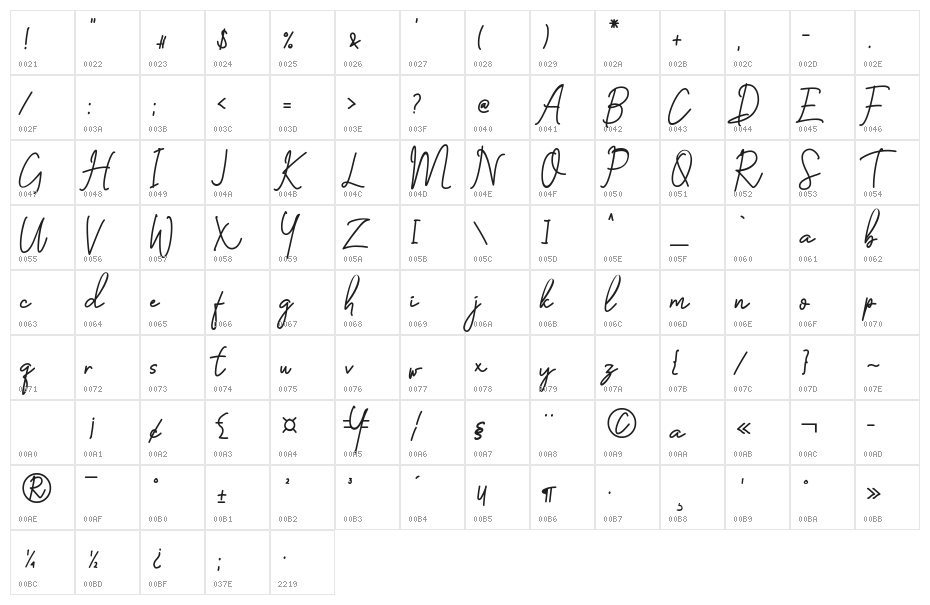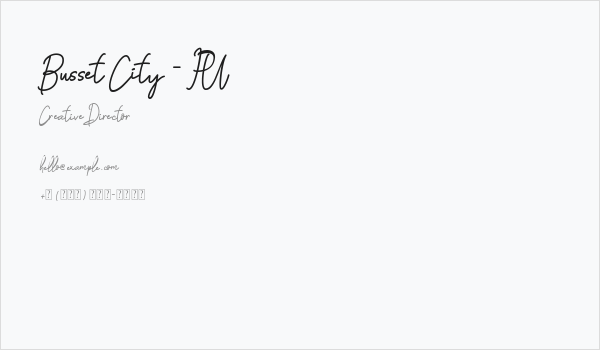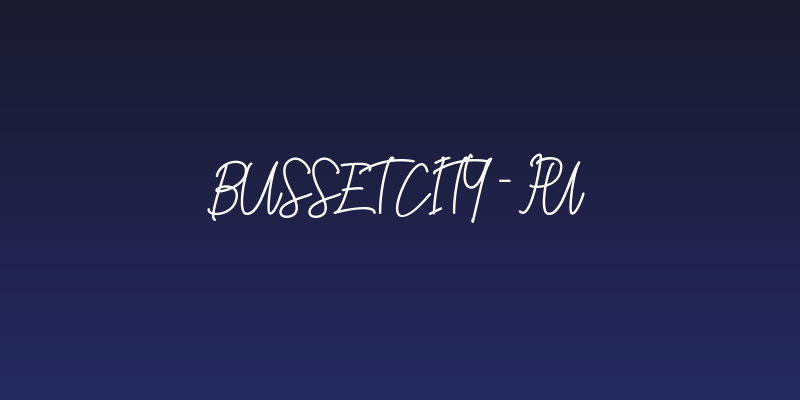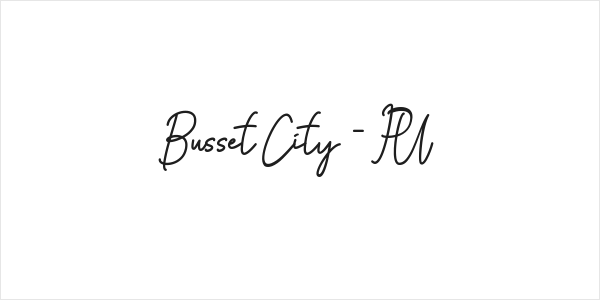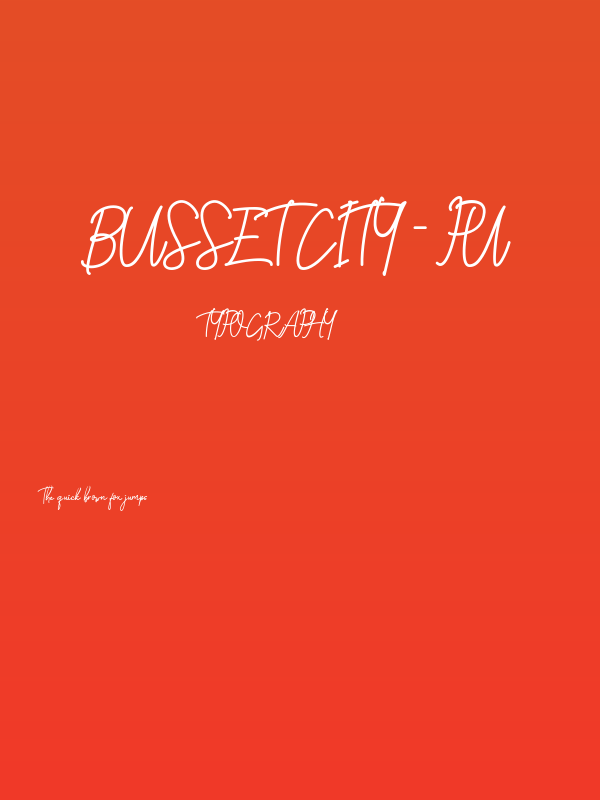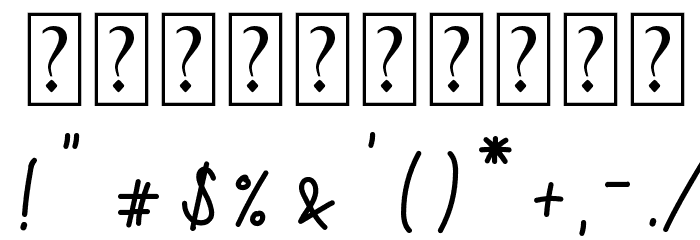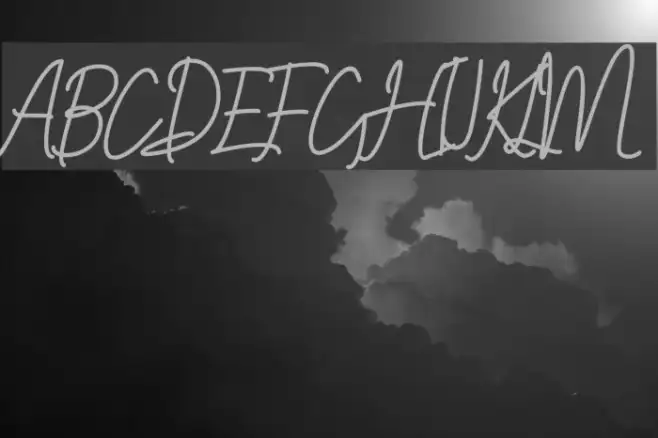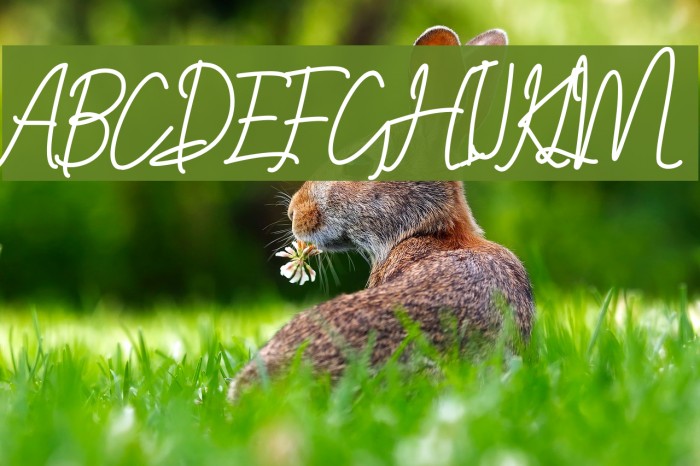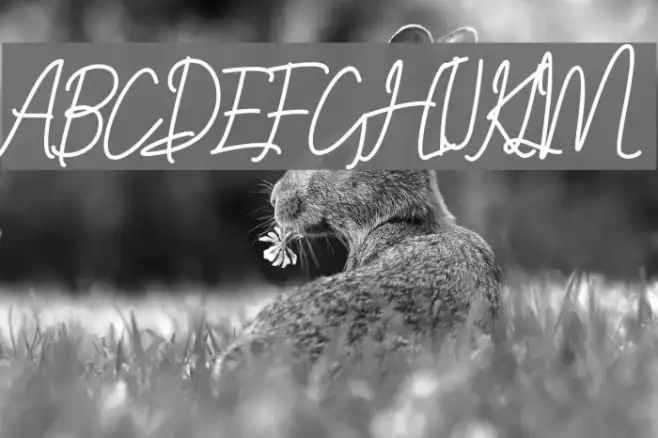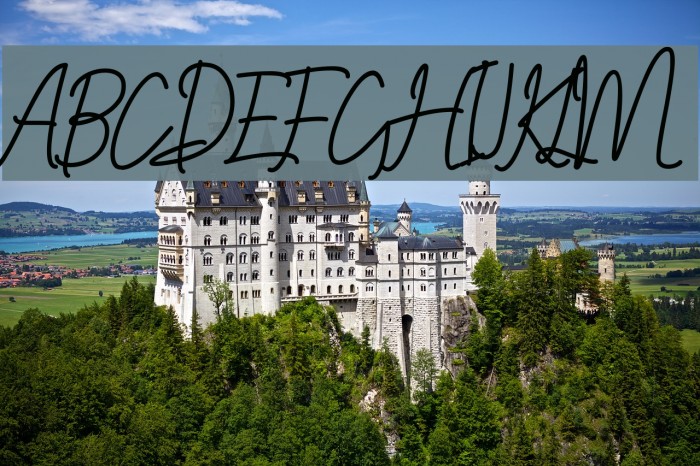
Busset City - PU Font
| Gesamtstil | Casual, Playful |
| Anwendungsfall | Logos, Invitations, Greeting Cards |
| Vorgeschlagene Projekte | Ideal for personal branding, invitations, greeting cards, and creative projects that require a personal touch. |